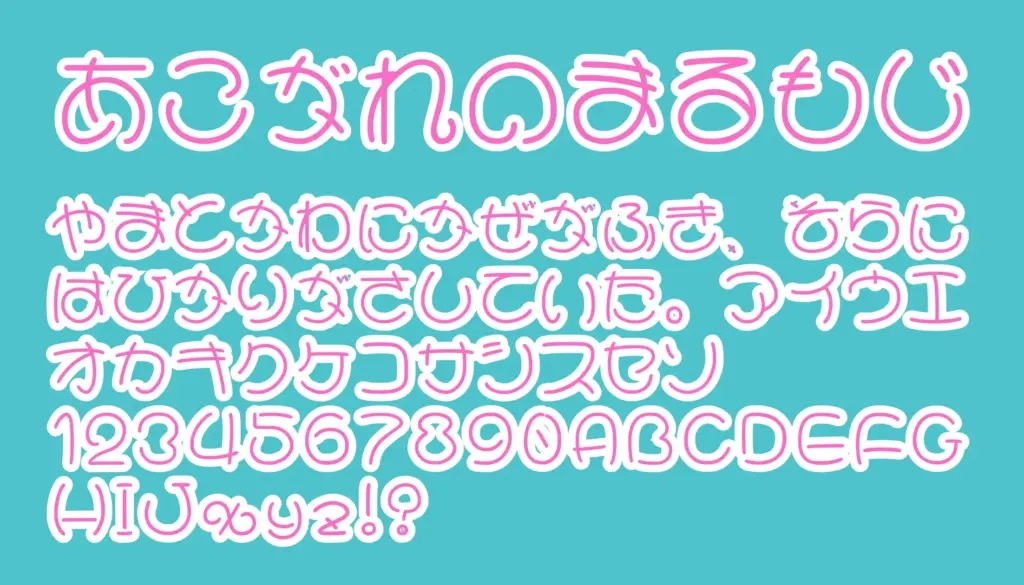
ひらがな・カタカナ・アルファベットがすべて“まるく・やさしく・個性的”にデザインされた混植対応フォントです。丸文字系の中でも特に筆圧の軽さやポップさが際立っており、手書き風のようなラフさも兼ね備えています。かわいらしさと視認性のバランスが良く、POP、うちわ文字、推し活グッズなど幅広い用途にフィットします。
あこがれのまるもじ